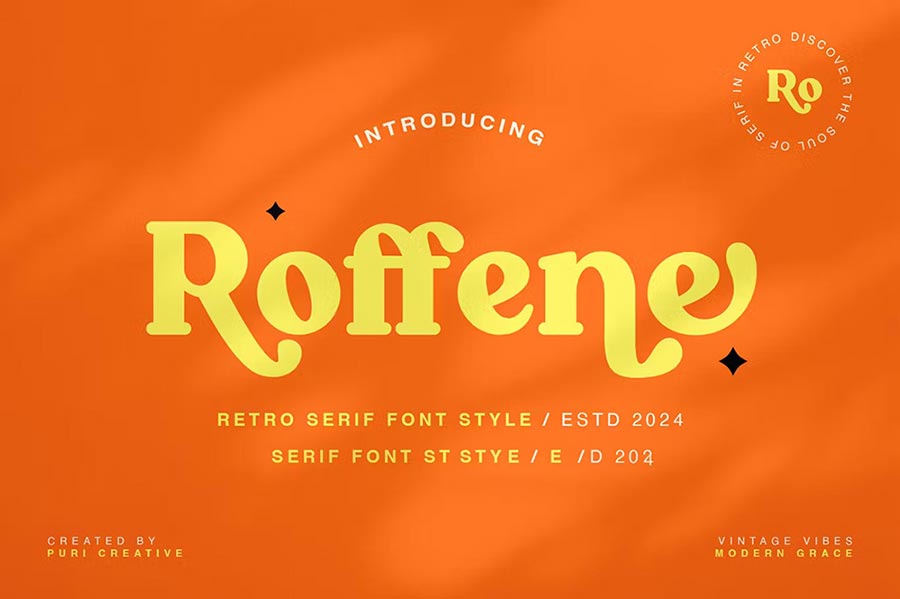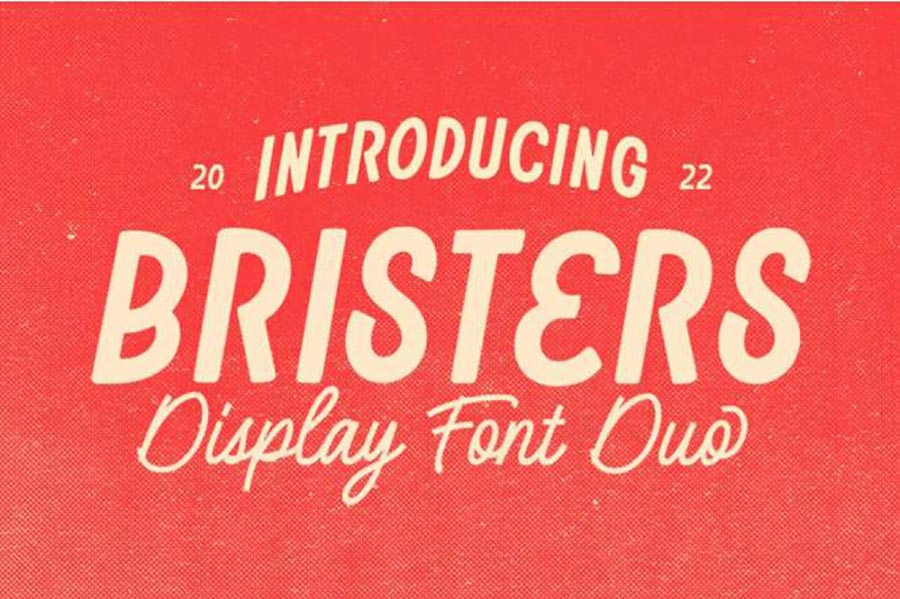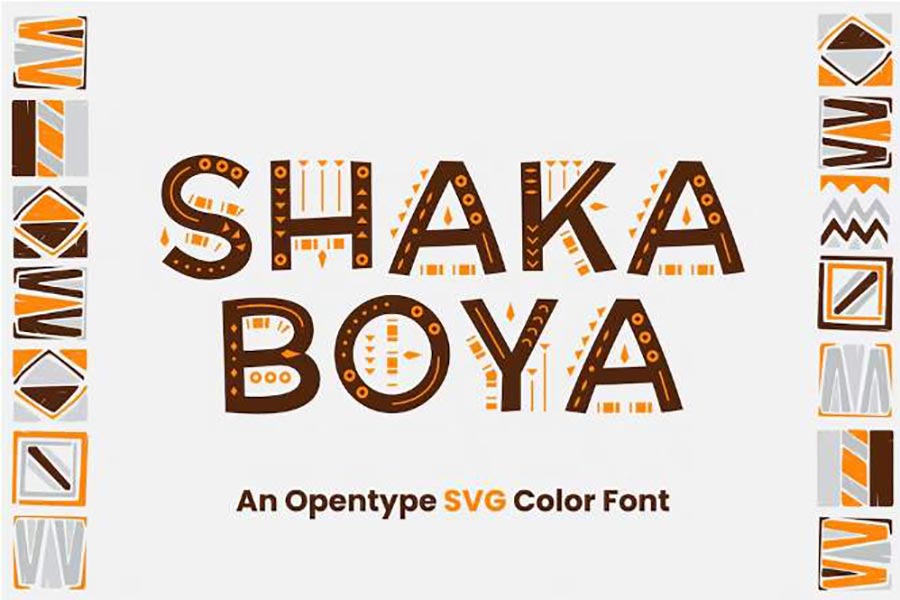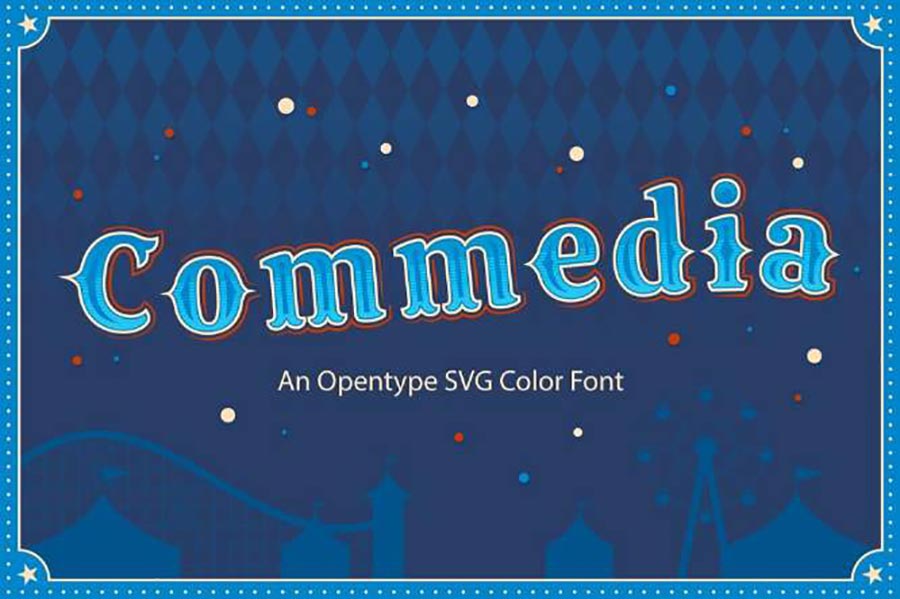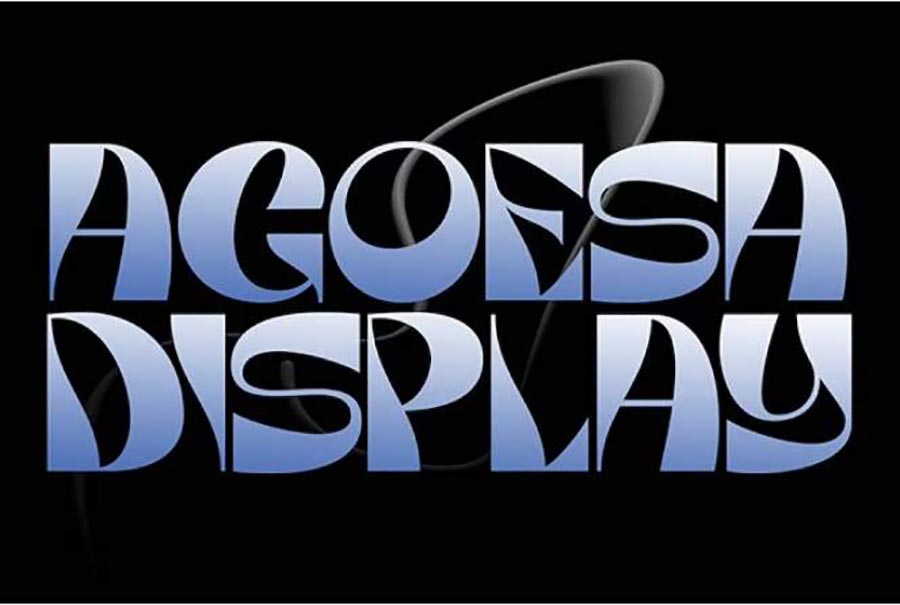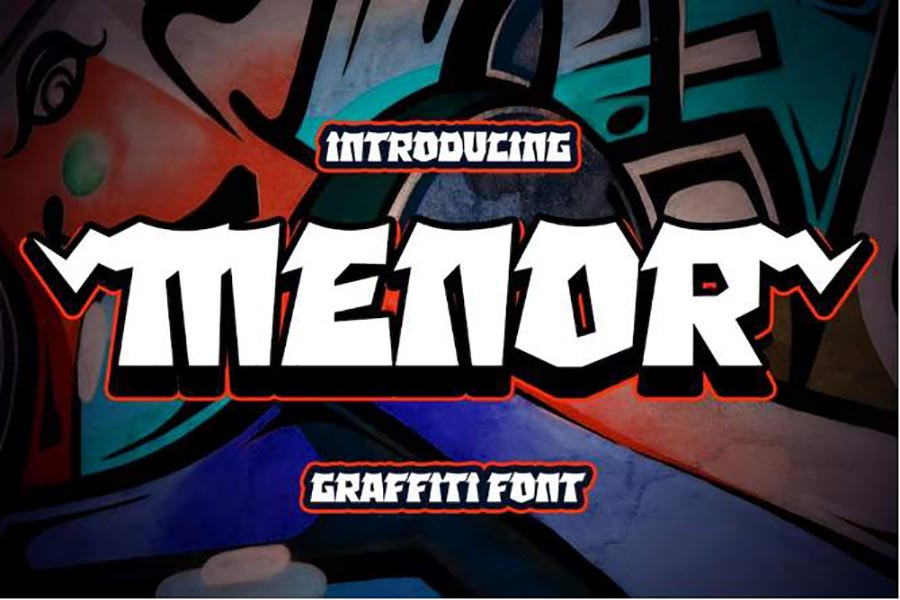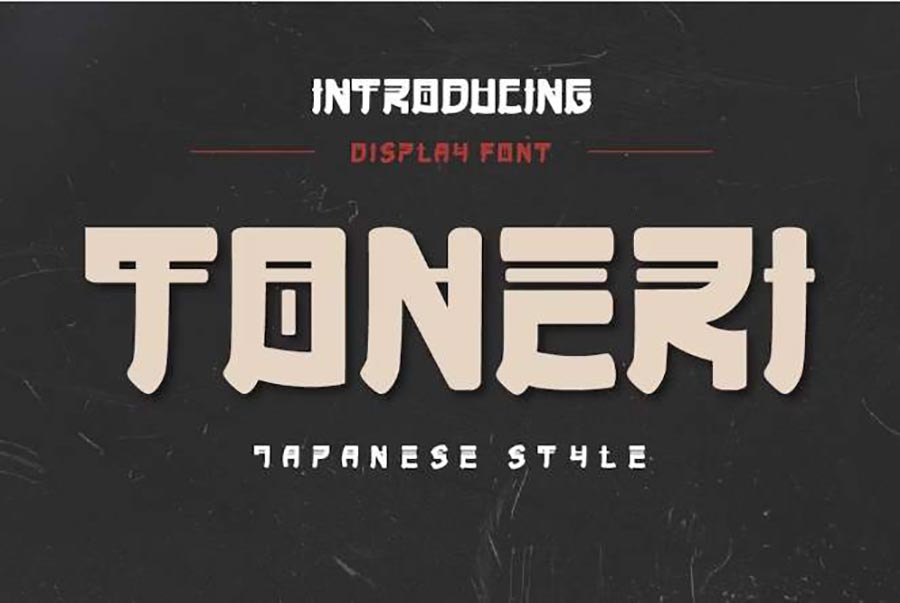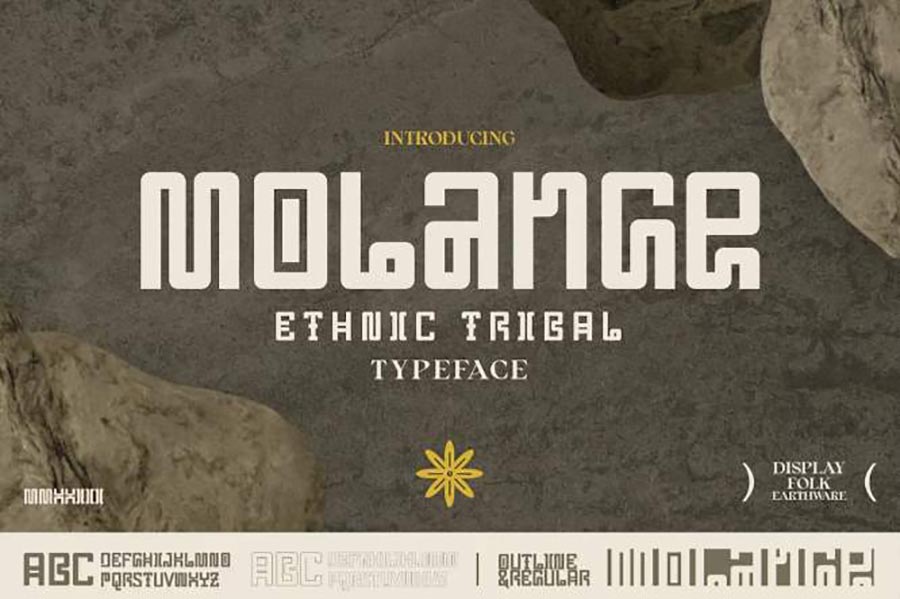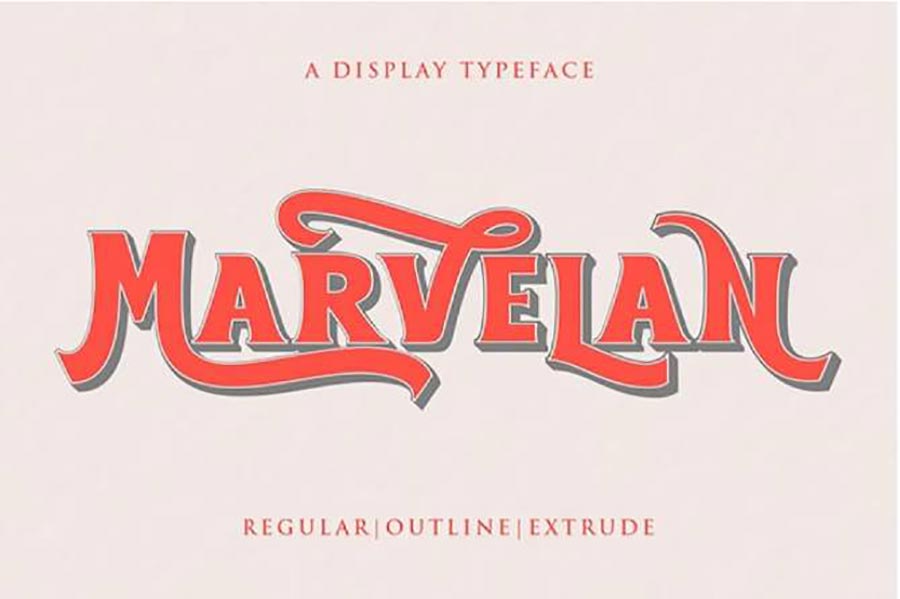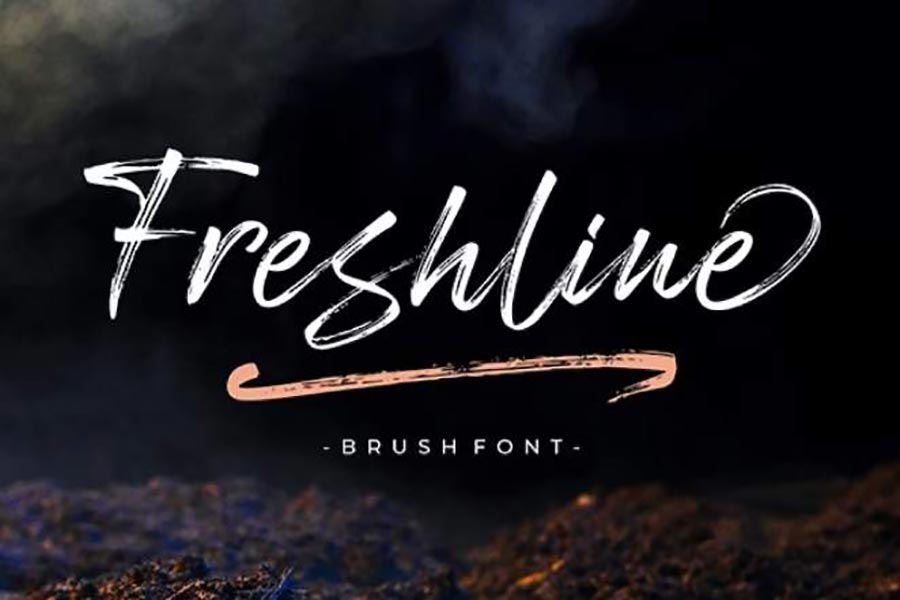
Font chữ Latin luôn là sự lựa chọn hoàn hảo cho những ai đang tìm kiếm sự tinh tế và chuyên nghiệp trong thiết kế. Với bộ font chữ Latin đẹp và chất lượng từ Sadesign.vn, bạn sẽ có trong tay công cụ mạnh mẽ để nâng tầm các dự án sáng tạo của mình. Điều đặc biệt là bạn có thể tải xuống miễn phí chỉ với vài bước đơn giản.
Tầm Quan Trọng Của Font Chữ Latin
Font chữ Latin không chỉ đơn thuần là những ký tự đẹp mắt, mà còn thể hiện sự chuyên nghiệp và sáng tạo trong từng chi tiết. Chúng đặc biệt phù hợp cho các thiết kế:
• Logo thương hiệu: Mang lại sự sang trọng và dễ nhận diện.
• Thiết kế poster: Tạo điểm nhấn thu hút ánh nhìn.
• Sản phẩm in ấn: Đảm bảo độ sắc nét và rõ ràng.
• Nội dung số: Phù hợp với cả website và ứng dụng di động.
Bộ font chữ Latin không chỉ giúp truyền tải thông điệp mà còn góp phần tạo nên cảm xúc cho người xem.
Mẹo Sử Dụng Font Chữ Latin Hiệu Quả
1. Phối Hợp Các Loại Font
Kết hợp font Serif và Sans-serif để tạo sự cân bằng giữa cổ điển và hiện đại.
2. Ưu Tiên Đọc Dễ Dàng
Khi thiết kế nội dung lớn, hãy chọn các font dễ đọc để đảm bảo truyền tải thông điệp hiệu quả.
3. Kiểm Tra Tương Thích
Đảm bảo font chữ bạn sử dụng tương thích với ngôn ngữ hoặc ký tự đặc biệt cần thiết.